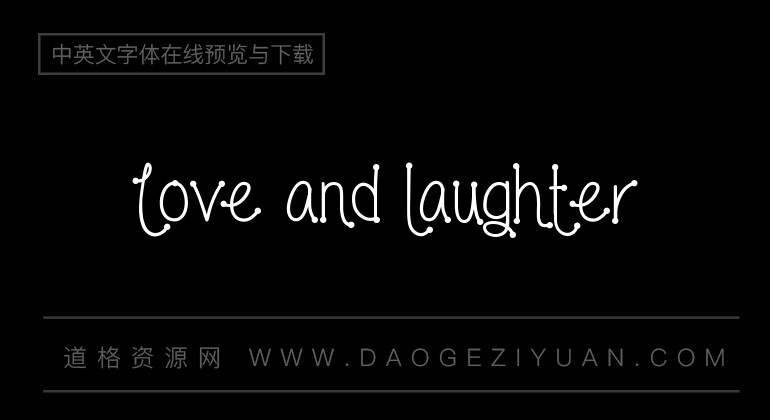
Love and Laughter字体是一款优雅的手写字体,由英国设计师Gemma O’Brien专门为爱情和欢笑而设计。它有着柔和的节奏,温暖的气息,以及优雅的曲线。它的字体特点是有着柔和的曲线,每一个字母都有着它自己特有的细节,而且每一笔画都有着自己的节奏。Love and Laughter字体可以用于手写爱情祝福卡片,日记,婚礼和其他礼仪场合。内容介绍
Love and laughter是一款非常不错的手写艺术字体,具有很好的视觉感,适合于文化类的宣传设计、商业类品牌的广告和产品包装设计以及个性化文字排版等较多场景。